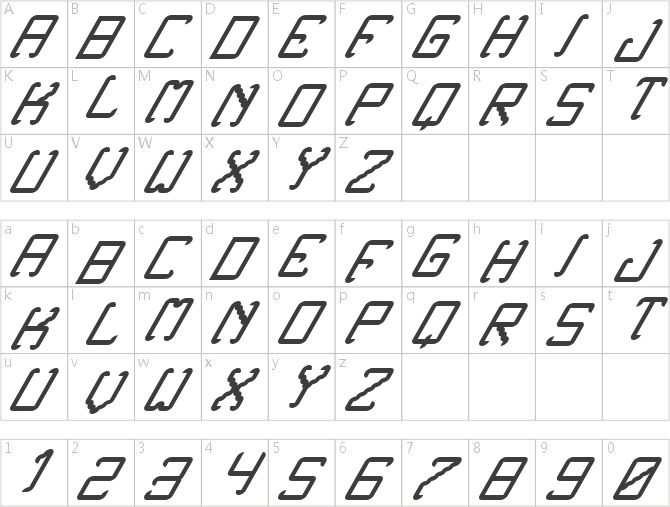
Noxtrey-Auf-tfb-extra-Italic 詳情頁
Noxtrey-Auf-tfb-extra-Italic字體字庫是一款讓人賞心悅目、百看不厭的英文字體,適合各類廣告和產(chǎn)品包裝設(shè)計應(yīng)用,字體大小0.01MB,格式為ttf字體,上傳用戶是W^xzj,作者/版權(quán)方為未知